Презентація на тему плакат і його види шрифт
1 Плакат і його види шрифт
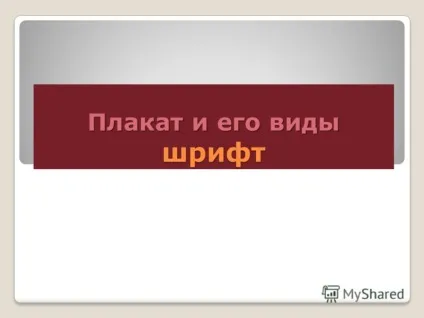
2 плакат Шрифтової плакат - поширений вид наочної агітації. Як особливий вид графічного мистецтва плакат існує з 2-ї половини 19ст. До цього плакатом називали агітаційні гравюри великого розміру. Мистецтво плаката в наші дні многожанровое
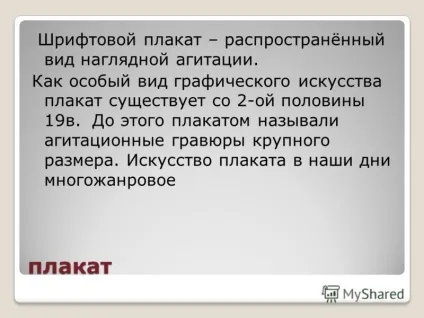
4 вимоги до плакату Специфіка художньої мови плаката визначається тим, що він повинен сприйматися на великій відстані, привертати увагу, сенс зображеного повинен відразу кидатися в очі Зображення та шрифт повинні показати ідею плаката. Складно вибрати шрифт, який в кожному окремому випадку найбільш доцільний. Колір шрифту привертає увагу і викликає особливе ставлення до зображення, представленого на плакаті.
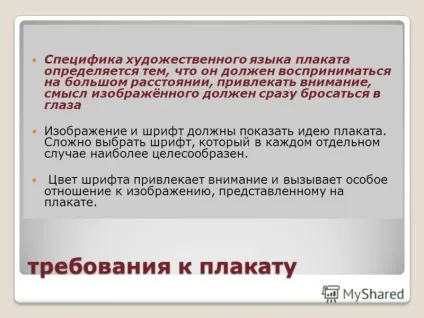
5 Види шрифтів Старословянскіе, без зарубок, із зарубками, альтернативні, брендові, буквиця, східні, готичні, графіті, декоративні, заголовні, мудрі, комічні, комп'ютерні, контурні, машинописні, моноширинних, об'ємні інші, святкові, ретро, рукописні самиепопулярние., трафаретні, жахливі, КО18
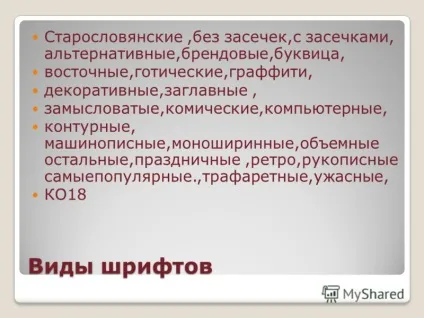
7 Першими українськими сатиричними політплакатамі можна назвати лубки, а пізніше - ростопчінская афіші, що роз'яснюють москвічамполітіческій момент 1812 року. У дореволюціоннойУкаіни політичний плакат вперше досяг значного розвитку в роки першої світової війни. Громадянська війна породила сатиричні ОкнаРОСТА - оригінальну форму швидкострільного плаката, озивається на злобу дня не тільки зрозумілим, в міру умовним малюнком, але і віршованим текстом. Тут на допомогу приходив народний гумор: казки, байки, приказки, прислів'я, а також досвід сатиричної журнальної графіки періоду революції рік
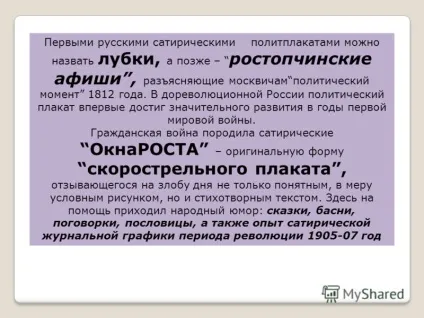
8 Історія На плакат звернули увагу такі видатні художники, як П.Гаварні, Г.Доре, Ж.-І.Гранвіль. Плакати, сповіщають про вихід у світ журналів (Гранвиль - Карикатюр) і книг (Доре - Гаргантюа і Пантагрюель, Гаварни - романи А.Дюма), найчастіше виставлялися в вітринах книжкових магазинів. У Німеччині в 1848 р на плакаті, названому Бойовий плакат, зображувалася боротьба демократії з реакцією. До кінця XIX століття, коли Ж.Шере розробив архітектоніку, формальну мову плаката (лаконічність, стислість думки, пластичний знак, що тяжіє до узагальненості і ритмування форми), плакат заявив про себе як вид мистецтва з величезними можливостями. В цей час до театрального плакату, чи не позбавленому гумору, а часом і гротеску, звернулися Тулуз-Лотрек і А.Стейнлен
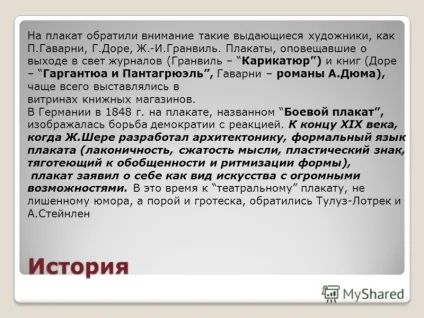
11 Політичний плакат В роки Великої Вітчизняної війни сатиричний плакат став мало не провідним видом мистецтва, поряд з карикатурою, благо висміювати ворога і закликати на боротьбу з ним дійсно справа свята. Об'єктів для сатири було досить - тупа фашистська система висувала вождів, зовнішній вигляд і справи яких самі просилися на посміховисько. Тут виділялися роботи Кукриніксів, що потрапили в чорний список нацистів. У 1956 р В.Бріскін і К.Иванов створили перший сатиричний агитплакат
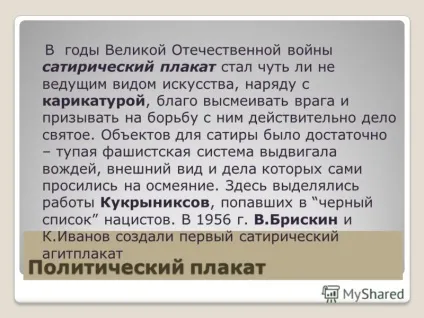
12 У мексиканському місті Канкун проходила конференція COP16, присвячена проблемам Глобального Потепління. А в рамках цієї конференції проходить Одинадцята бієнале сучасного плаката. Плакатом проти глобального потепління (Екологічний плакат)
13 Роботи учасників «плакати проти глобального потепління» Роботи учасників «плакати проти глобального потепління»
15 Плакати проти наркоманії - пропаганда здорового способу життя Плакати проти наркоманії можна вважати одним з первинних методів профілактики наркозалежності серед молоді.
17 В мистецтві плаката нічого не пропадає. Давно померлі течії і стилі весь час відроджуються. Що вже говорити про прийоми, відпрацьованих в газетній та журнальній карикатурі. На міжнародних варшавських виставках плаката європейці вперше побачили роботи американця С.Стейнберга і японця Ш.Фукуди - блискучих карикатуристів, що не підпали під вплив новітніх комп'ютерних технологій. У машини немає і ніколи не буде почуття гумору, що додає індивідуальну нетерпимість художнику.